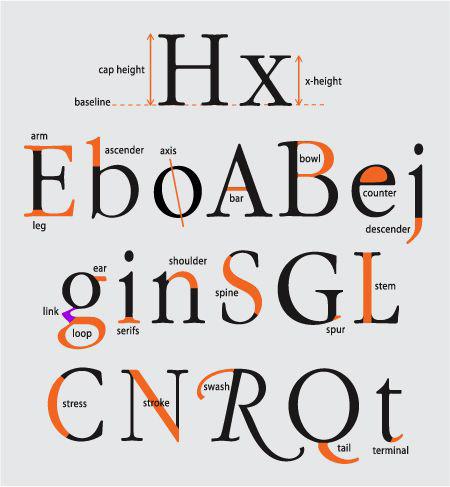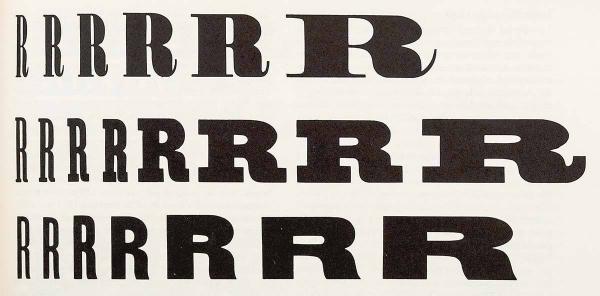
Γράμματα Τυπογραφία. I. Η ανατομία του γράμματος ΙΙ. Γράμμα ΙII. Λέξη IV. Πηγές & προγράμματα σχεδιασμού γραμμάτων
2 Γράμματα - Τυπογραφία {Γ εξάμηνο σπουδών, κατεύθυνση Γραφιστικής} {2} Τυπογραφία «Η αρχιτεκτονική των ιδεών και η δημιουργία της γλώσσας», αποκαλύπτοντας τον ρόλο της τυπογραφίας στη δόμηση της αφήγησης - δημιουργώντας διανοητικό χώρο μέσα από τον οποίο κινείται ο αναγνώστης. «Η διαμόρφωση της εμπειρίας». Η διερεύνηση της ιδέας ότι η μορφή επικοινωνίας του μηνύματος επηρεάζει την πρόσληψη του περιεχομένου από τον αναγνώστη. «Η διαχείριση των γραμμάτων». Η σπουδαιότητα της οργανωτικότητας του σχεδιαστή και η σχέση της με τη δημιουργία δομών. «Η μηχανή της μάθησης». Πως η τυπογραφία ενδυναμώνει τους καλλιεργημένους αναγνώστες. «Η αποκρυσταλλωμένη επέκταση της μνήμης». Η σπουδαιότητα της καταγραφής και της διατήρησης των ιδεών στον αναστοχασμό. «Ζωγραφίζοντας με λέξεις». Η τυπογραφία ως εκφραστική τέχνη, όπου το συναισθηματικό περιεχόμενο των ιδεών επικοινωνείται μέσα από τον σχεδιασμό της μορφής των λέξεων. Baines P., Haslam A. (2002). Type and typography. Νew York: Watson-Guptill Publications.
3 I. Η ανατομία του γράμματος {3}
4 Γράμματα - Τυπογραφία {Γ εξάμηνο σπουδών, κατεύθυνση Γραφιστικής} {4} I. Η ανατομία του γράμματος Κάθετος & διαγώνιος κορμός (stem): η κύρια κάθετη ή διαγώνια κοντυλιά ενός γράμματος. Οριζόντια κεραία / βραχίονας (crossbar): η οριζόντια κοντυλιά η οποία ενώνει τους δύο κάθετους (όπως: Τ, F, Η) ή διαγώνιους (όπως: Α, Δ) κορμούς. Κοίλο μέρος / λωβός (bowl): το καμπύλο ή ελλειπτικό σχήμα που διαμορφώνουν οι κύριες κοντυλιές ορισμένων γραμμάτων, όπως στα Β, Θ, Ρ, Φ, β, δ, d, ρ, e, c, p μεταξύ άλλων). Οφθαλμός (counter): ο λευκός χώρος που περιβάλλεται από το κοίλο μέρος ενός γράμματος. ΤΦFHA ΔV ΒΘ0βδρεe κοίλο μέρος οφθαλμός
5 Γράμματα - Τυπογραφία {Γ εξάμηνο σπουδών, κατεύθυνση Γραφιστικής} {5} I. Η ανατομία του γράμματος Προεκτάσεις: οι κατιούσες κοντυλιές (descenders) και οι ανιούσες κοντυλιές (ascenders) που εκτείνονται αντίστοιχα κάτω και πάνω από το μέσο ύψος των πεζών γραμμάτων. ζ η ι ρ δ γ λ ξ
6 Γράμματα - Τυπογραφία {Γ εξάμηνο σπουδών, κατεύθυνση Γραφιστικής} {6} I. Η ανατομία του γράμματος Γραμμή βάσης (baseline): Ο νοητός οδηγός πάνω στον οποίον ευθυγραμμίζονται όλα τα γράμματα κάθε στίχου (αράδας). Γραμμή ύψους ανιουσών κοντυλιών Γραμμή κεφαλαίων γραμμάτων Γραμμή ύψους πεζών γραμμάτων Γραμμή βάσης Η Α δ γ λ ο Γραμμή βάθους \κατιουσών κοντυλιών
7 Γράμματα - Τυπογραφία {Γ εξάμηνο σπουδών, κατεύθυνση Γραφιστικής} {7} I. Η ανατομία του γράμματος Γραμμή ύψους πεζών γραμμάτων (mean line / x-height): Ορίζει την απόσταση από τη γραμμή βάσης έως την κορυφή των πεζών γραμμάτων χωρίς ανιούσες/κατιούσες προεκτάσεις (δηλ. των α, ε, ι, κ, ν, ο, π, σ, τ, υ, ω, a, c, e, i, m, n, o, r, s, u, v, w, x, z, κ.ά.). Σε αυτή ευθυγραμμίζονται και τα υπόλοιπα που έχουν αντίστοιχο σώμα (π.χ. β, γ, δ, λ, μ, ρ, φ, χ, ψ, b, d, g, h, j, k, p, q, y κ.ά.). Γραμμή ύψους των ανιουσών κοντυλιών (ascent line): Ορίζει την απόσταση από τη γραμμή ύψους των πεζών γραμμάτων έως την κορυφή των στοιχείων (π.χ. β, δ, ζ, θ, λ, ξ, b, d, f, h, k, l, κ.ά.). Δεν ταυτίζεται απαραίτητα με το ύψος των κεφαλαίων γραμμάτων (caps line). Γραμμή βάθους των κατιουσών κοντυλιών (descent line): Ορίζει την απόσταση από τη γραμμή βάσης έως το κατώτερο σημείο των στοιχείων (π.χ. γ, ζ, μ, ξ, ρ, φ, χ, ψ, g, j, p, q, y κ.ά.).
8 Γράμματα - Τυπογραφία {Γ εξάμηνο σπουδών, κατεύθυνση Γραφιστικής} {8} I. Η ανατομία του γράμματος Ο άξονας του γράμματος (axis): Καθορίζεται από την κλίση της κοντυλιάς, ή αλλιώς από τη γωνία της γραφίδας κατά την κίνηση του χεριού. Τον βρίσκουμε ενώνοντας τα άνω και κάτω σημεία έντασης ενός καμπύλου γράμματος.
9 Γράμματα - Τυπογραφία {Γ εξάμηνο σπουδών, κατεύθυνση Γραφιστικής} {9} I. Η ανατομία του γράμματος Ακρεμόνες (πατούρες - serif): Οι καταληκτικές κοντυλιές που προστίθονται στις άκρες των κοντυλιών ενός γράμματος. Διακρίνονται σε: συνεχείς ακρεμόνες (transitive), οι οποίοι σχεδιάζονται σαν φυσική απόληξη του κορμού του γράμματος (συνήθως μονόπλευροι), και τους ασυνεχείς (reflexive) στους οποίους ο κορμός ολοκληρώνεται και ο ακρεμόνας σχεδιάζεται με μικρή στροφή της γραφίδας.
10 Γράμματα - Τυπογραφία {Γ εξάμηνο σπουδών, κατεύθυνση Γραφιστικής} {10} I. Η ανατομία του γράμματος Ακρεμόνες (πατούρες - serif) Κατά περίπτωση έχουμε τους: μονόπλευρους ακρεμόνες, όπως στην κορυφή των Γ, Τ, Ε, και τους αμφίπλευρους (bilateral), όπως στη βάση και κορυφή των Ι, Κ, Η, τη βάση του Α, κ.λπ.
11 Γράμματα - Τυπογραφία {Γ εξάμηνο σπουδών, κατεύθυνση Γραφιστικής} {11} I. Η ανατομία του γράμματος
12 ΙI. Γράμμα {12}
13 Γράμματα - Τυπογραφία {Γ εξάμηνο σπουδών, κατεύθυνση Γραφιστικής} {13} ΙΙ. Γράμμα 1α. Διαστάσεις ή μέγεθος των στοιχείων Ως μέγεθος των τυπογραφικών στοιχείων μετράμε το ύψος του νοητού παραλληλογράμμου που περιβάλλει κάθε γράμμα. Το πλάτος του πλαισίου είναι διαφορετικό ανάλογα με τον σχεδιασμό του κάθε χαρακτήρα και περιλαμβάνει τα πλευρικά περιθώρια σύμφωνα με την επιλογή του σχεδιαστή. Τετράγωνοι χώροι 10 στιγμών 14 στιγμών 24 στιγμών 30 στιγμών 36 στιγμών 48 στιγμών 60 στιγμών 72 στιγμών 82 στιγμών
14 Γράμματα - Τυπογραφία {Γ εξάμηνο σπουδών, κατεύθυνση Γραφιστικής} {14} ΙΙ. Γράμμα 1α. Διαστάσεις ή μέγεθος των στοιχείων ΠΡΟΣΟΧΗ! Σε διαφορετικές γραμματοσειρές τα ορατά στοιχεία μπορεί να έχουν διαφορετικό ύψος, αλλά το μέγεθός τους καθορίζεται από το νοητό πλαίσιο. Στο παράδειγμα, οι τέσσερεις γραμματοσειρές είναι του ίδιου μεγέθους (180 στιγμών), αλλά έχουν διαφορετικό ύψος των (ορατών) χαρακτήρων τους. Αυτό το περίπλοκο σύστημα μέτρησης πηγάζει από τότε που τα στοιχεία ήταν μεταλλικά και μετρούσαν το ύψος του μολυβένιου παραλληλεπίπεδου στην άκρη του οποίου βρισκόταν ανεστραμμένο το ανάγλυφο γράμμα. τετράγωνο 180 στιγμών Η Η H Η Arial 180 στιγμών Times 180 στιγμών Verdana 180 στιγμών Georgia 180 στιγμών
15 Γράμματα - Τυπογραφία {Γ εξάμηνο σπουδών, κατεύθυνση Γραφιστικής} {15} ΙΙ. Γράμμα 1β. Διαστάσεις ή μέγεθος Η μέτρηση γίνεται σε στιγμές (pt). Το σύστημα μέτρησης με στιγμές δημιουργήθηκε τον 19 ο αιώνα από τους Pierre Fournier & Francois Didot. Αντιστοιχία: 1 στιγμή = 0,375 χιλ. 12 στιγμές = 1 τετράγωνο (Cicero) = 4,5 χιλ. Η σύγχρονη Αγγλοσαξονική στιγμή έχει λίγο διαφορετικό μέγεθος και αντιστοιχεί σε 1/72 της ίντσας. {10 pt} Μια υπέροχη μέρα για να μάθουμε σχεδιασμό γραμμάτων. {12 pt} Μια υπέροχη μέρα για να μάθουμε σχεδιασμό γραμμάτων. {14 pt} Yπέροχη μέρα για να μάθουμε σχεδιασμό γραμμάτων. {20 pt} Yπέροχη μέρα για να μάθουμε σχεδιασμό γραμμάτων. {24 pt} Yπέροχη μέρα για να μάθουμε σχεδιασμό γραμμάτων. {30 pt} Yπέροχη μέρα για να μάθουμε σχεδιασμό γραμμάτων. {36 pt} Yπέροχη μέρα για να μάθουμε σχεδιασμό γραμμάτων. {42 pt} Yπέροχη μέρα για να μάθουμε σχεδιασμό γραμμάτων.